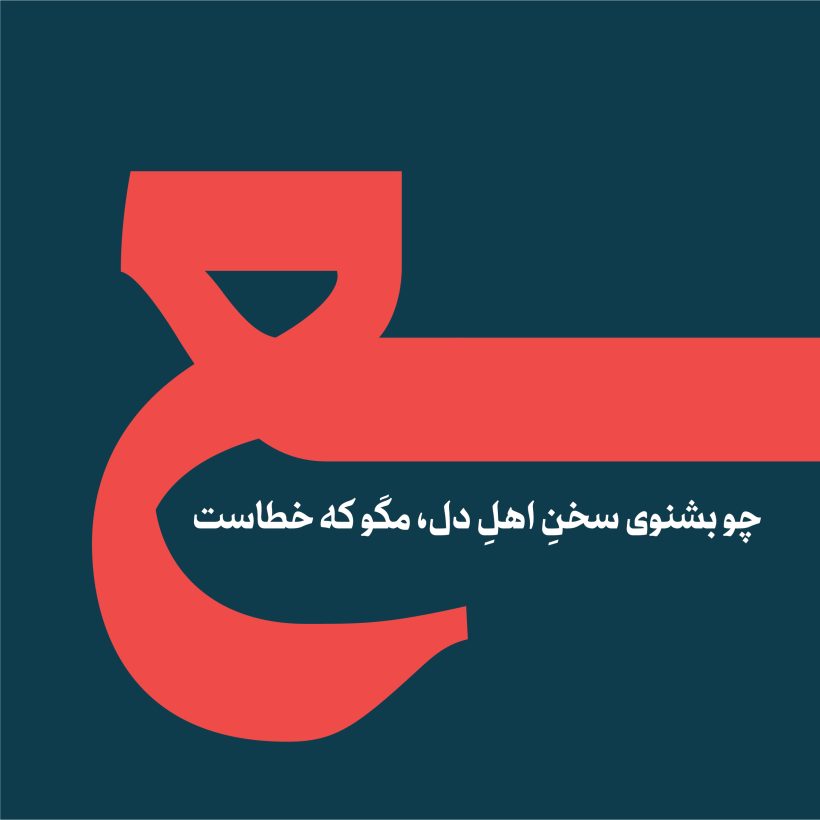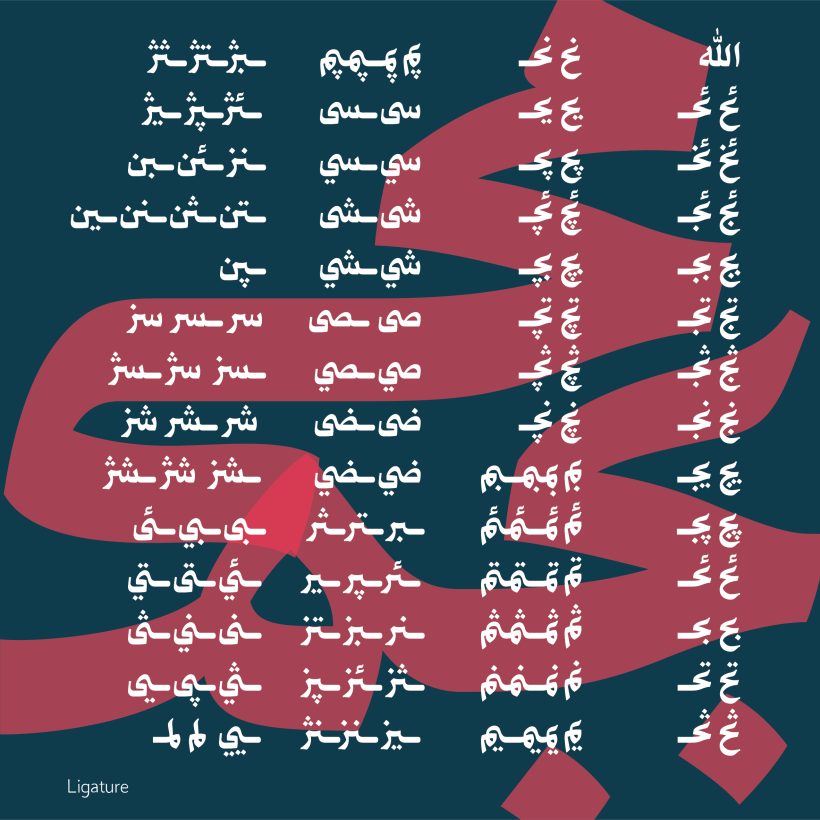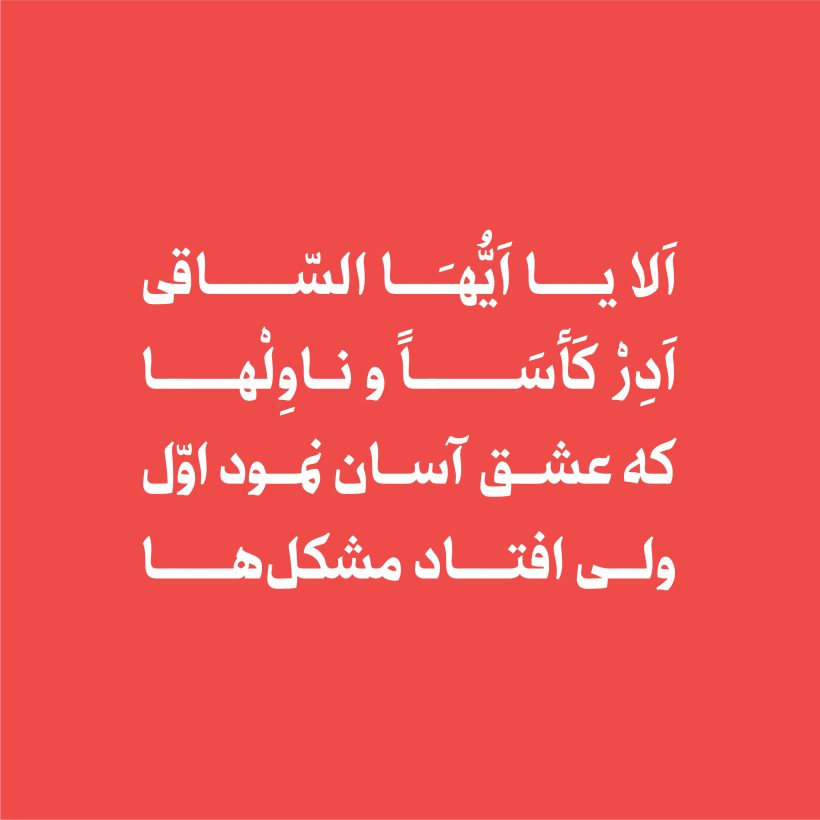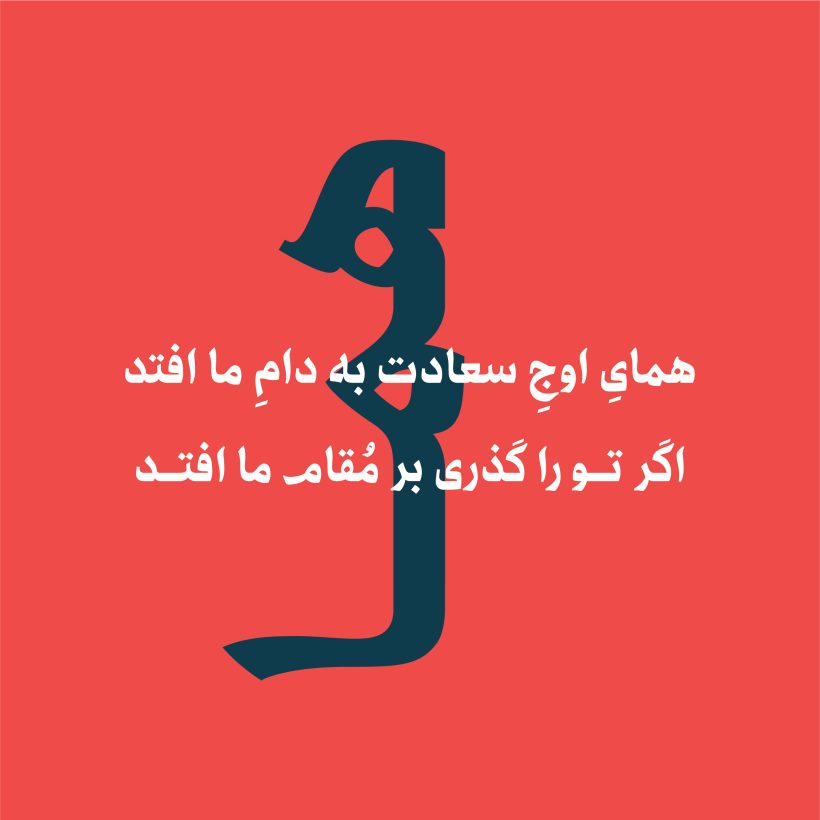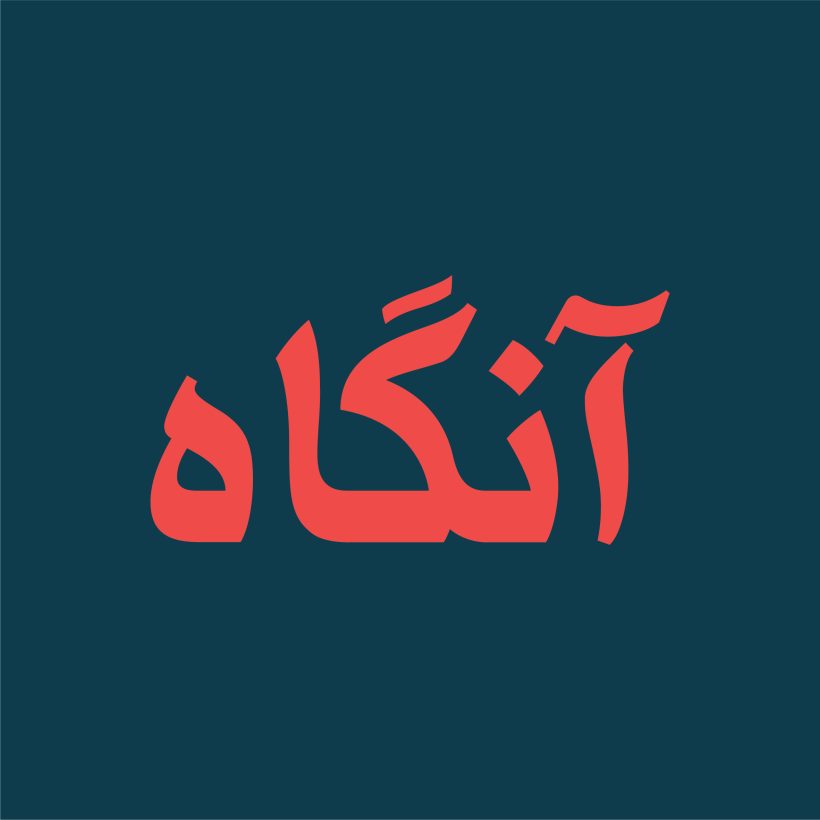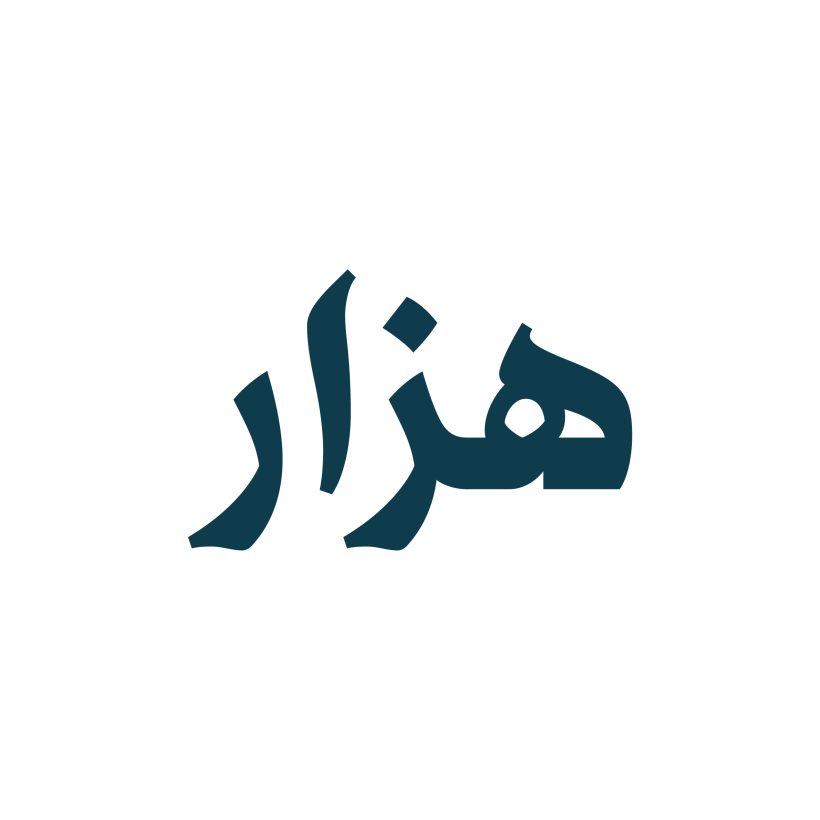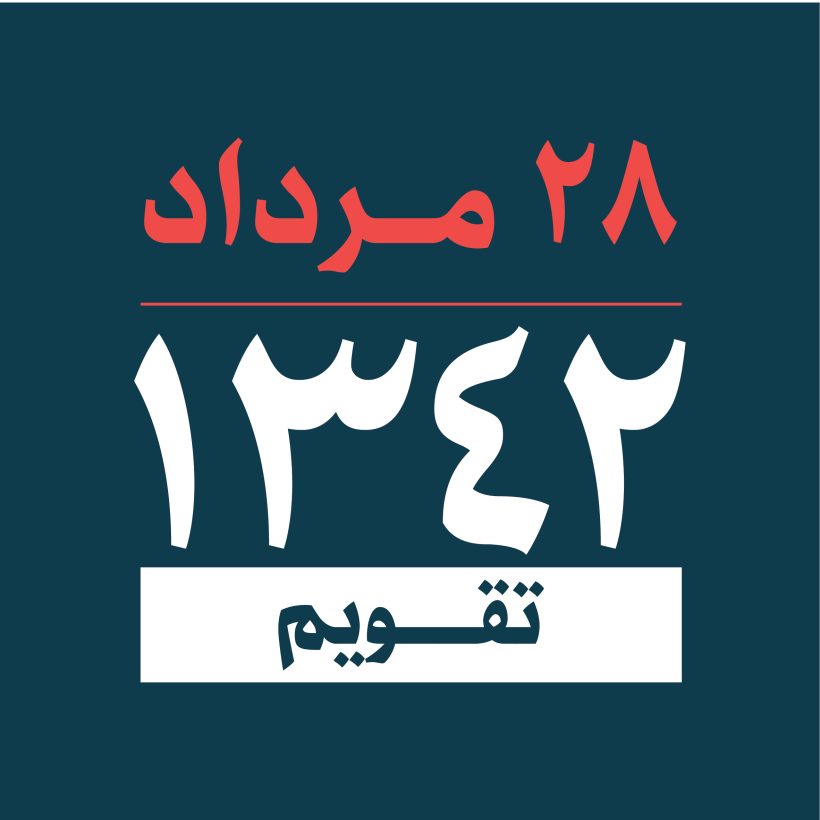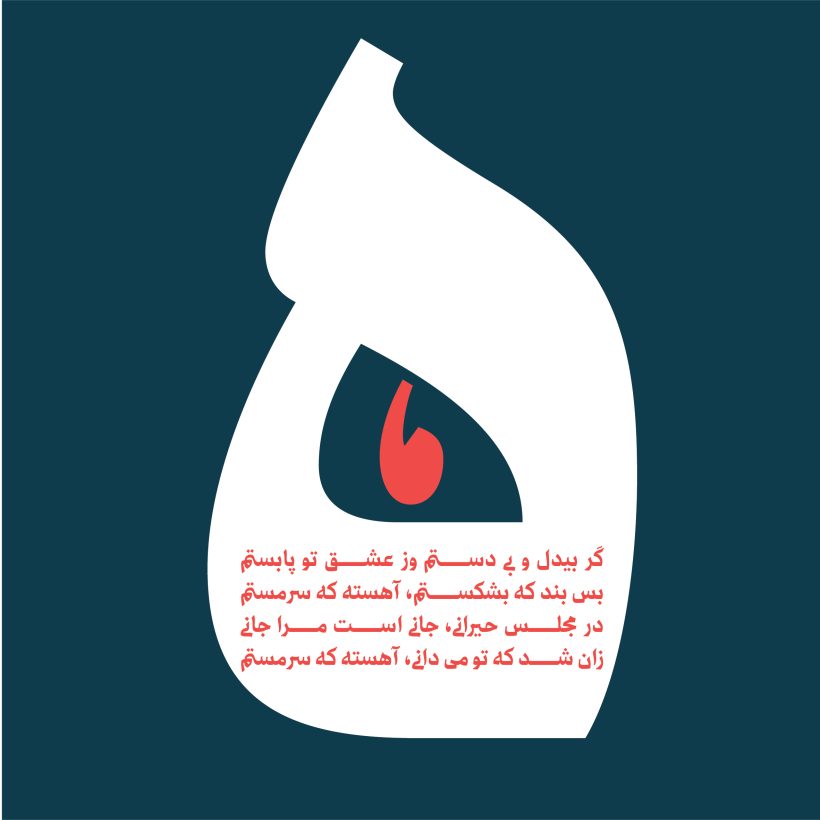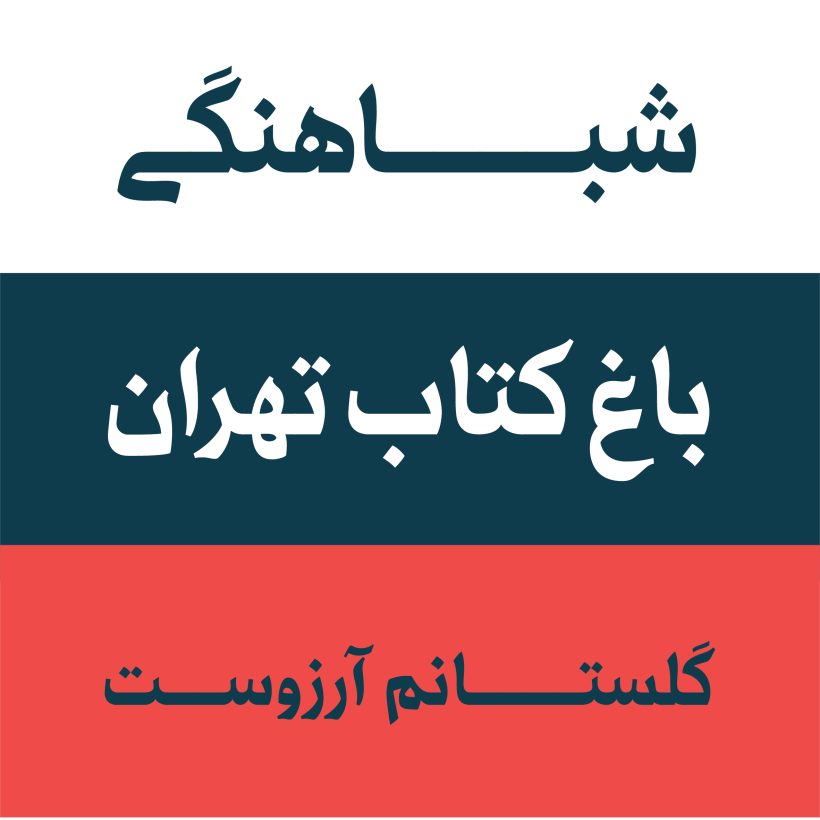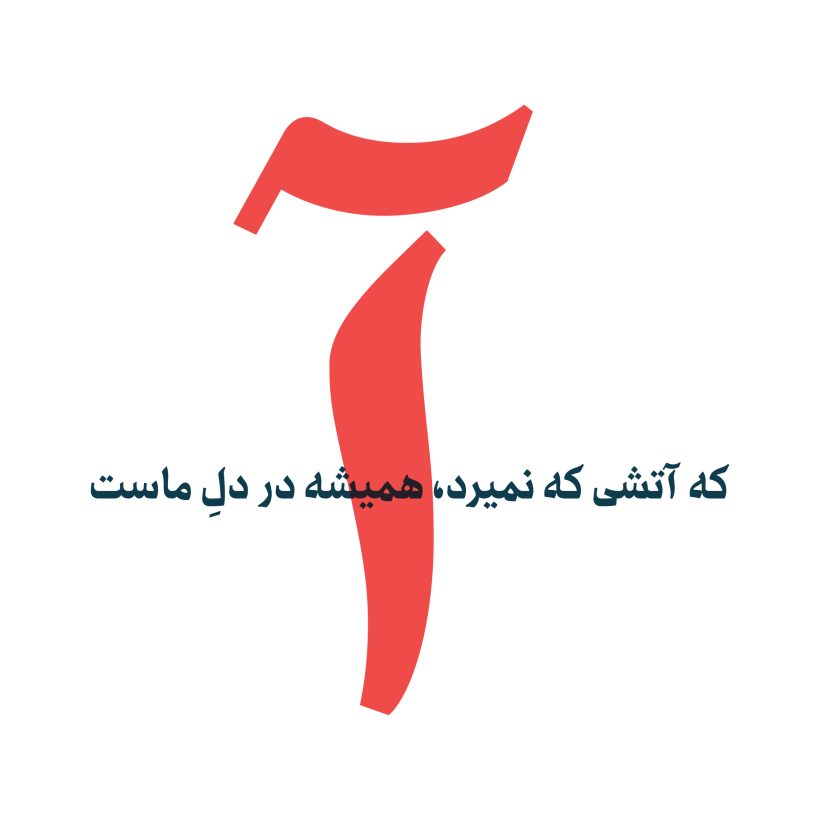
فونت طره
فونت طره برداشت و نگاهی نو به خوشنویسی سنتی است که با تلفیق خطوط نسخ و ثلث طراحی شده است. در این فونت تا حد ممکن سعی شده ظرافت ها و زیبایی های اصیل خوشنویسی سنتی حفظ گردد. یکی از ویژگی های اصلی فونت طره، شروع حرکت قلم در حروفی مانند الف، هاء، نون و .. است که با دانگ یا نسبت کم قلم به همراه کمی حالت خوشنویسانه طراحی شده است. در فونت طره حرکات مدور حروف روی خط کرسی با سطح زیاد همراه شده و اغلب حرکات حروف حول کرسی وسط استقرار یافته است.
طره فونت نمایشی و در یک وزن طراحی و اجرا است و برای عناوین و متون و سطرهای کوتاه مناسب است. از دیگر ویژگی های فونت طره، لیگیچر و کاراکترهای جایگزین حروف است که متناسب با رسم الخط خوشنویسی سنتی طراحی و ارائه شده است که به کاربران این امکان را  می‌دهد تا متناسب با نیاز خود، از کاراکترهای جایگزین و لیگیچر استفاده نماید.
فونت طره توسط معصومه مصلح و با مدیریت دیزاین صداقت جباری طراحی شده است.